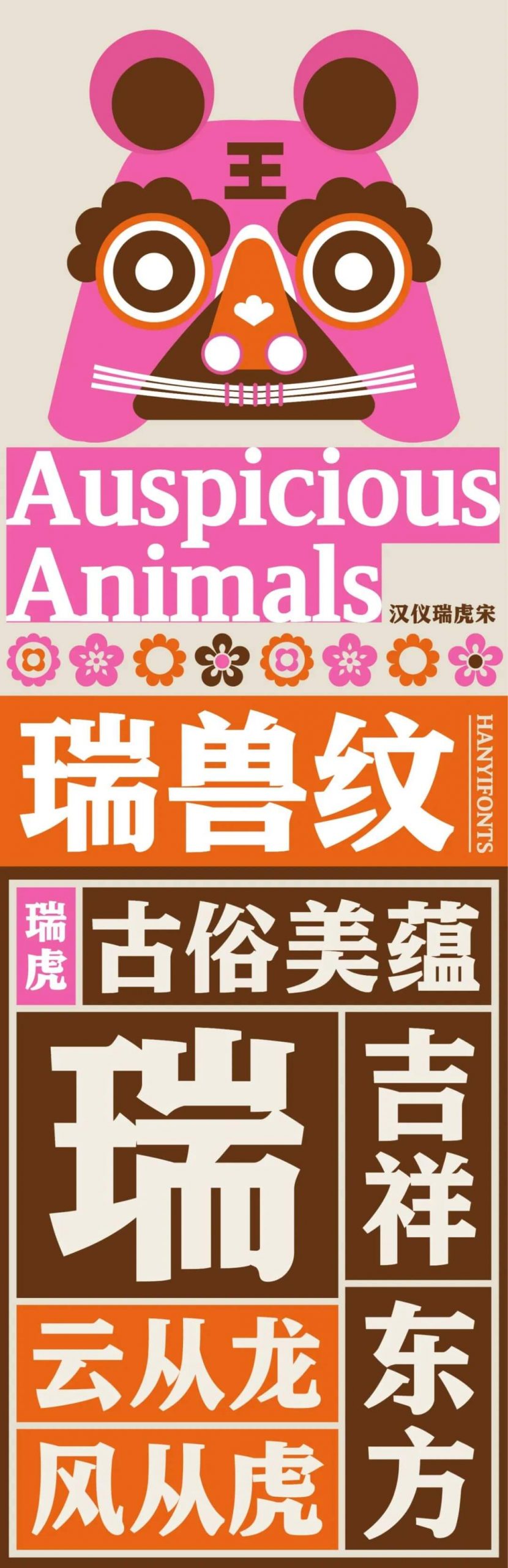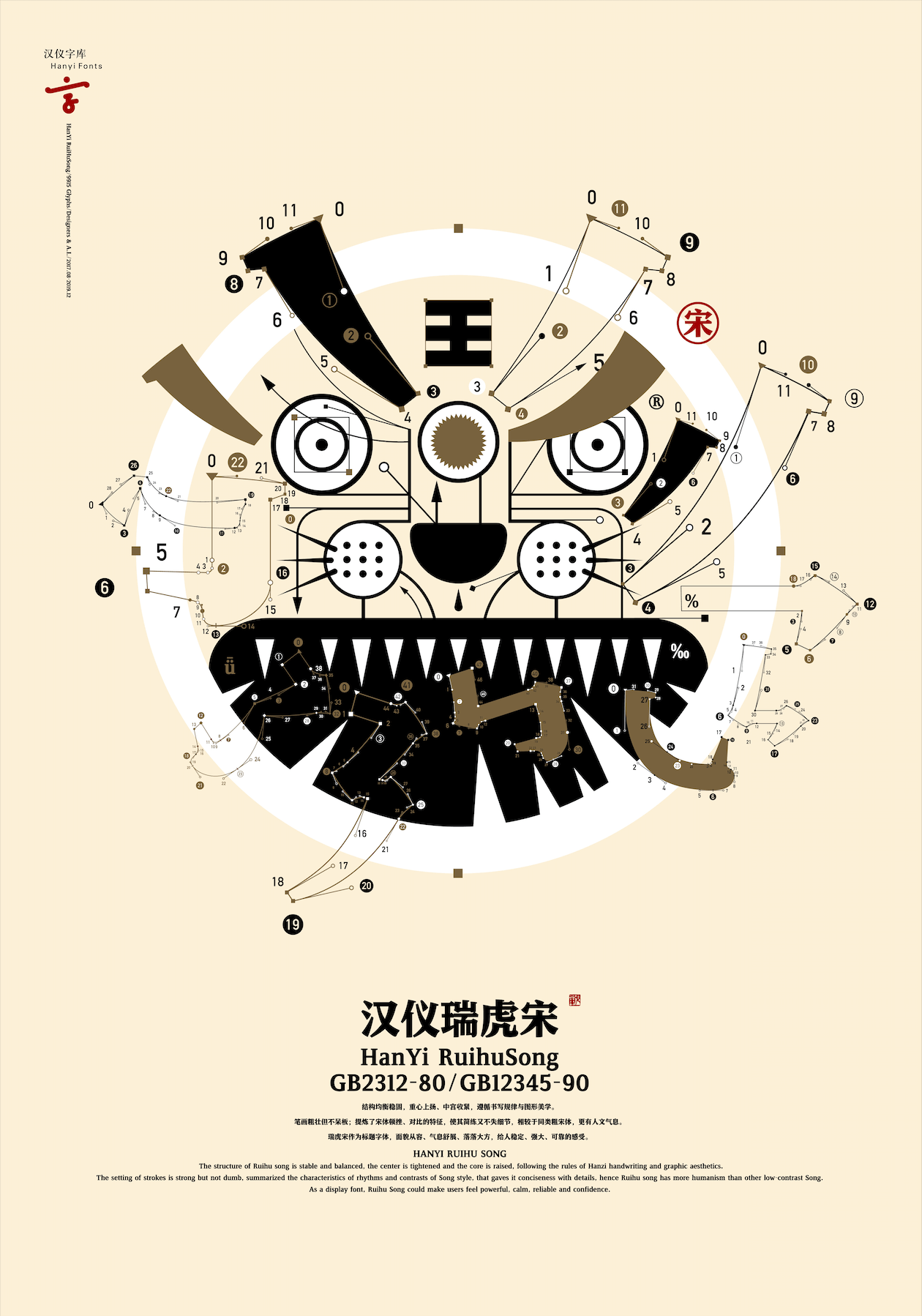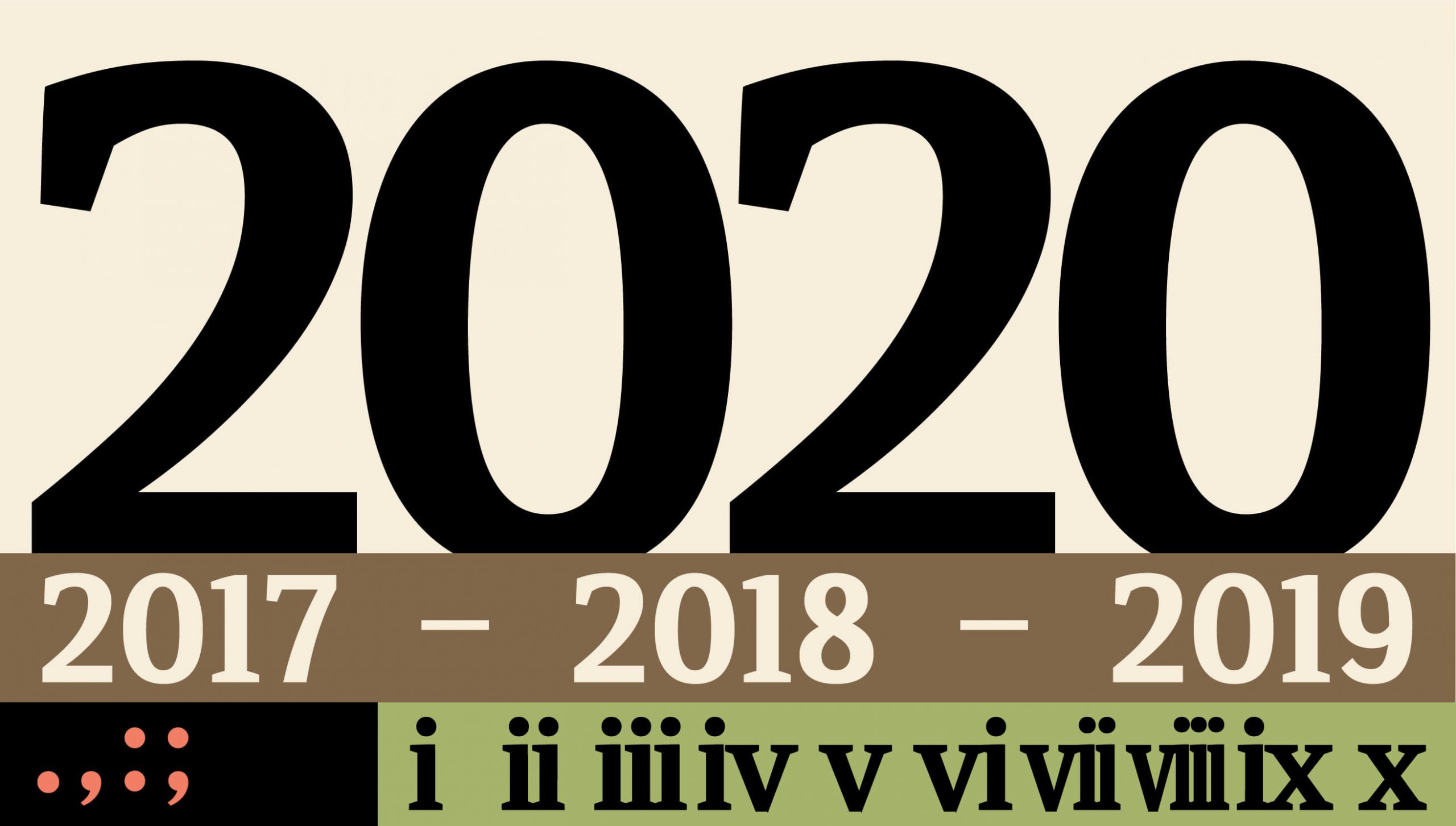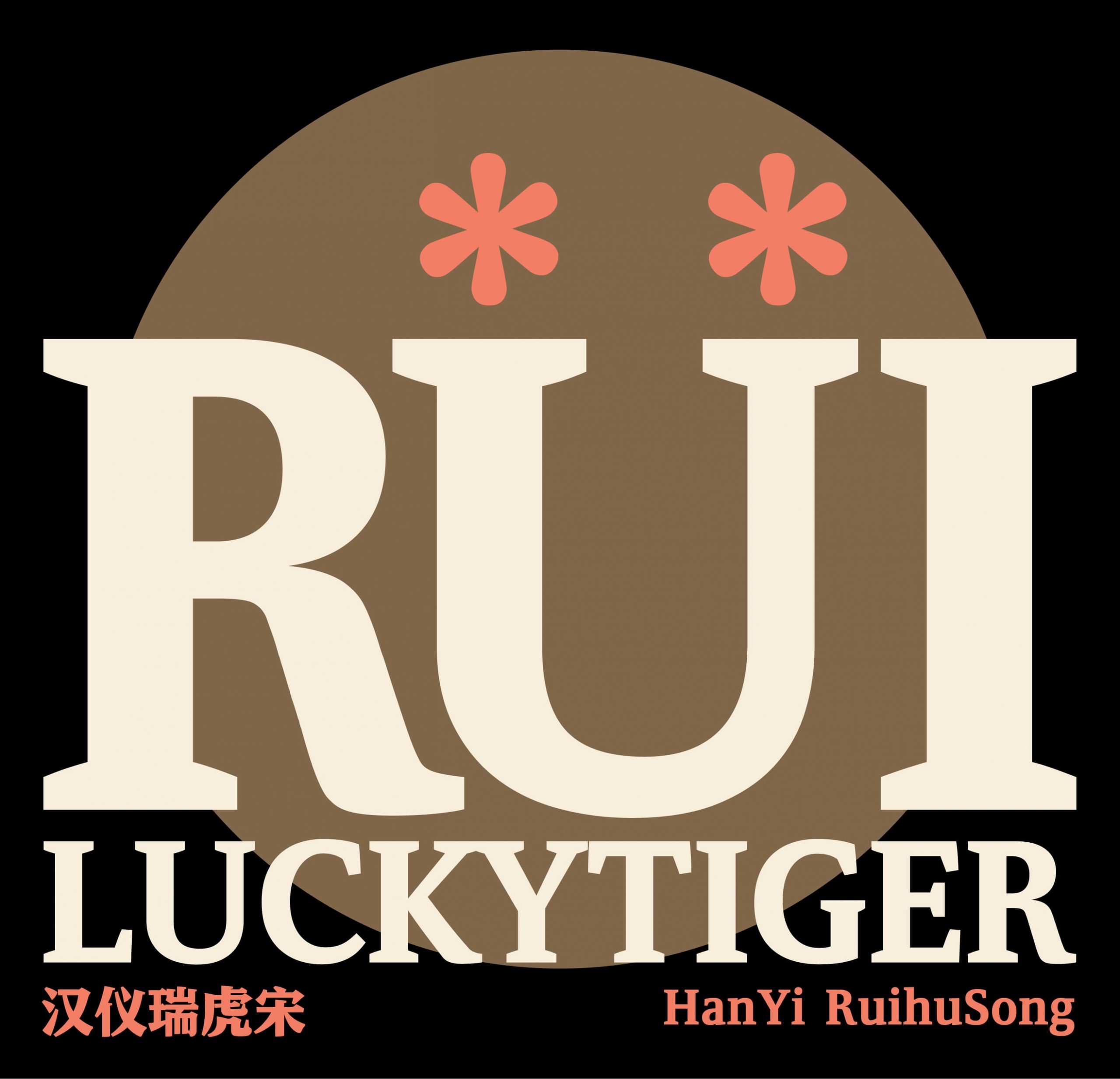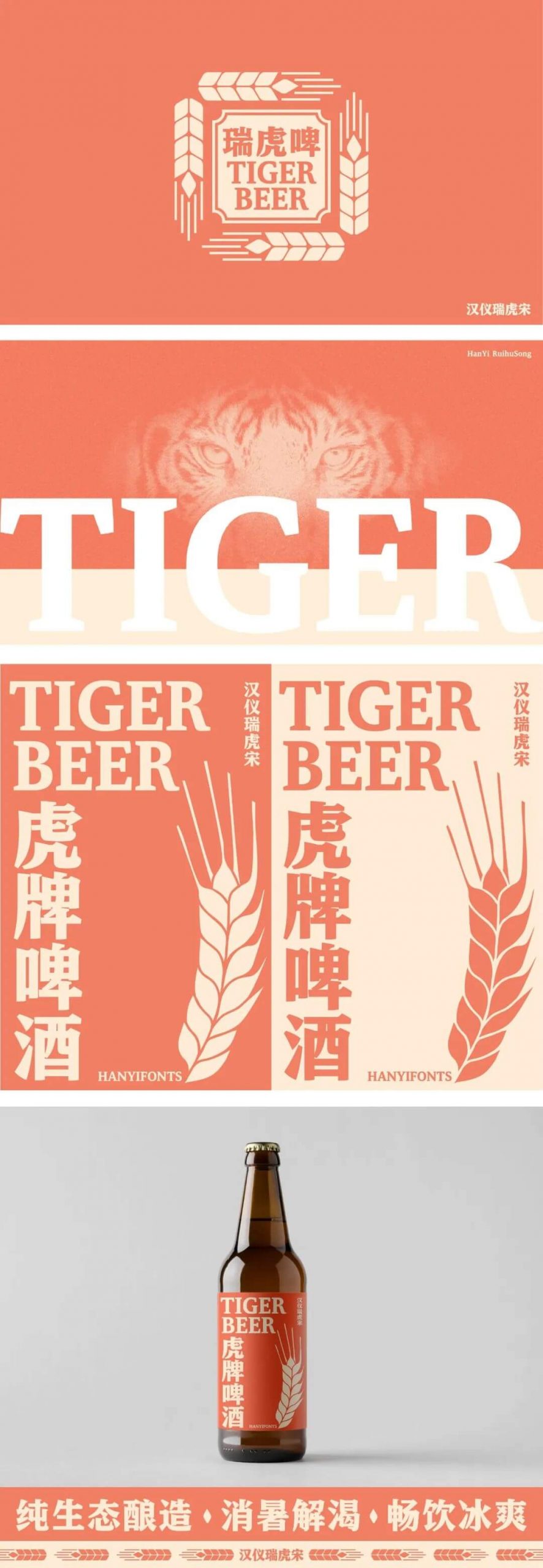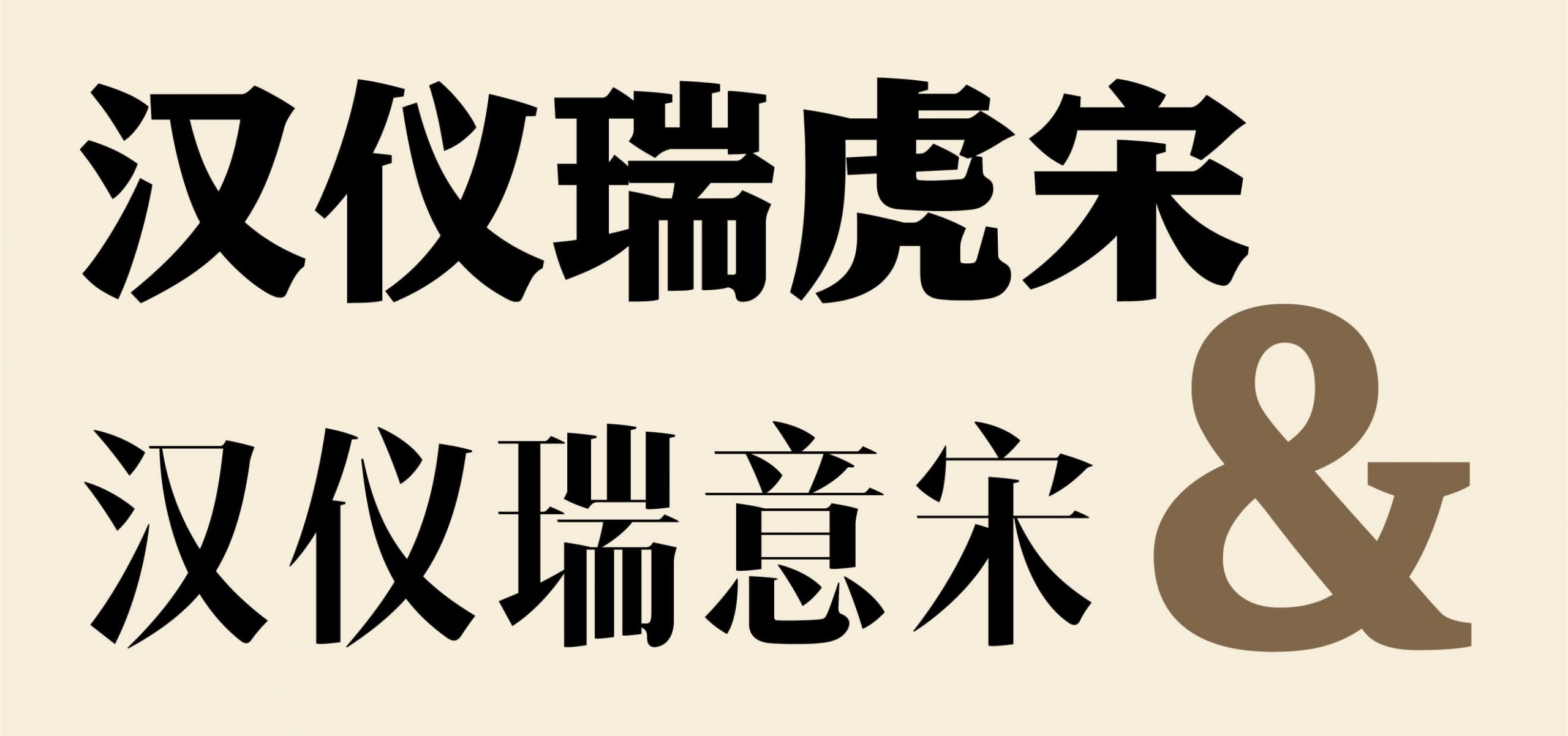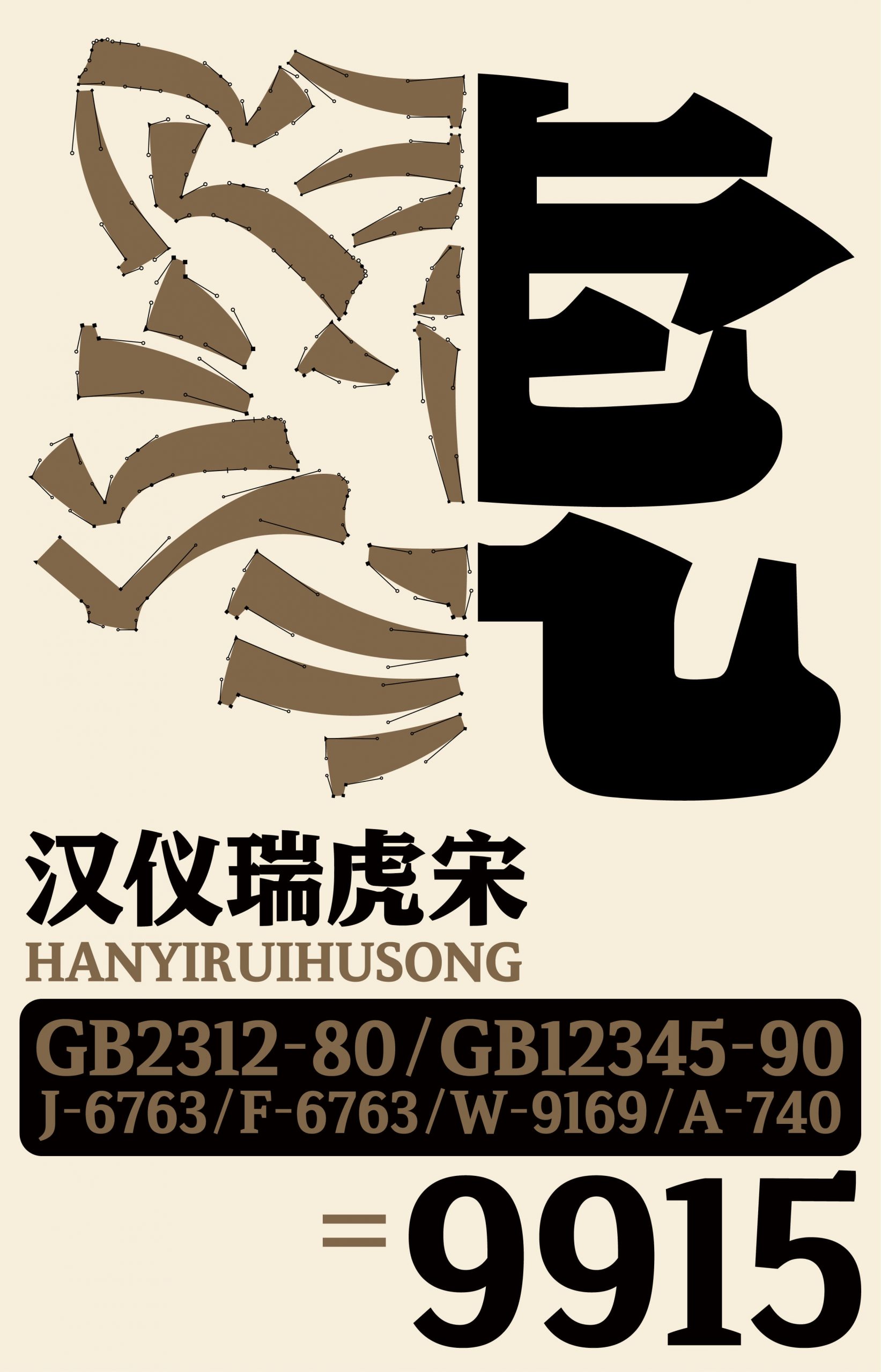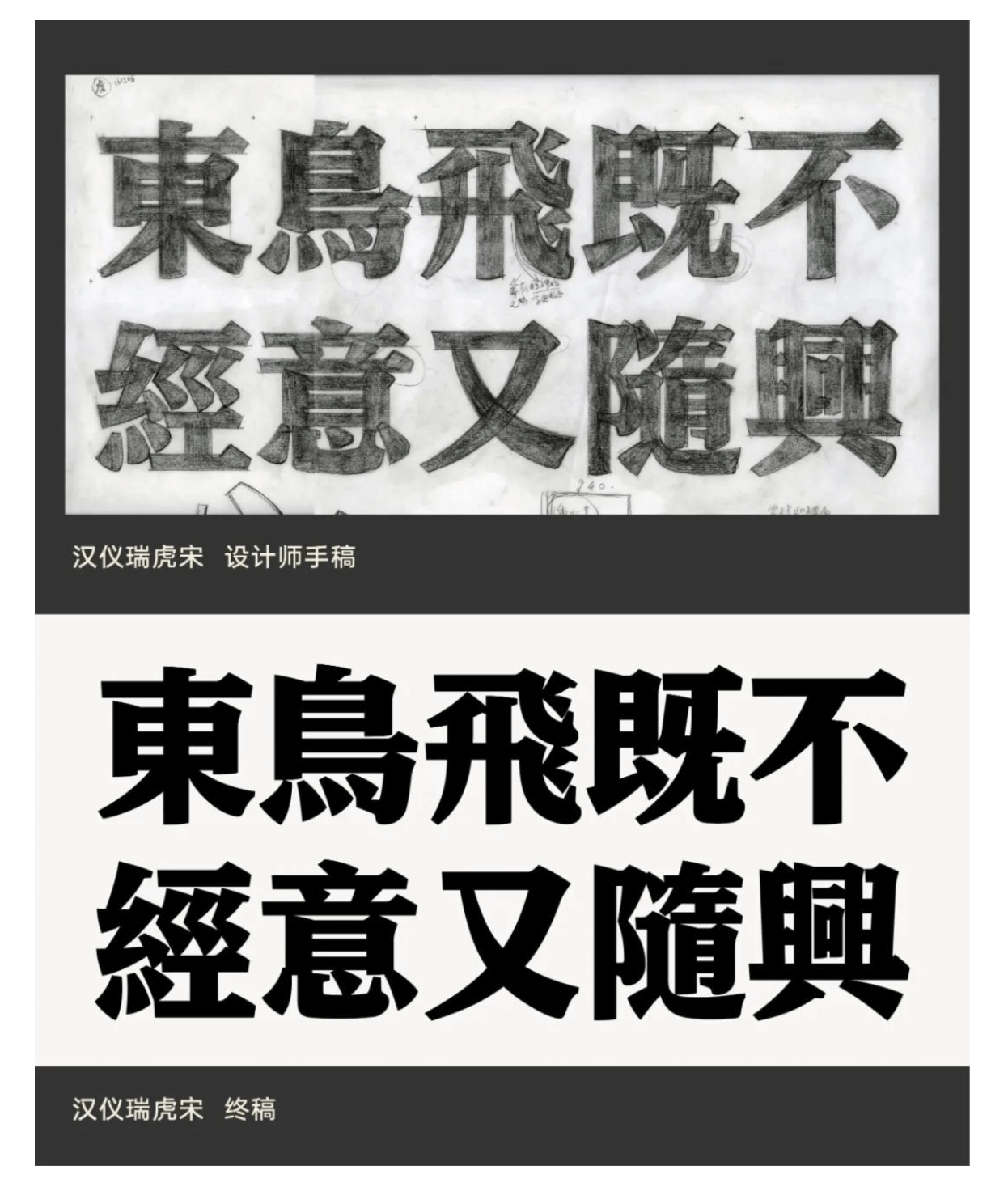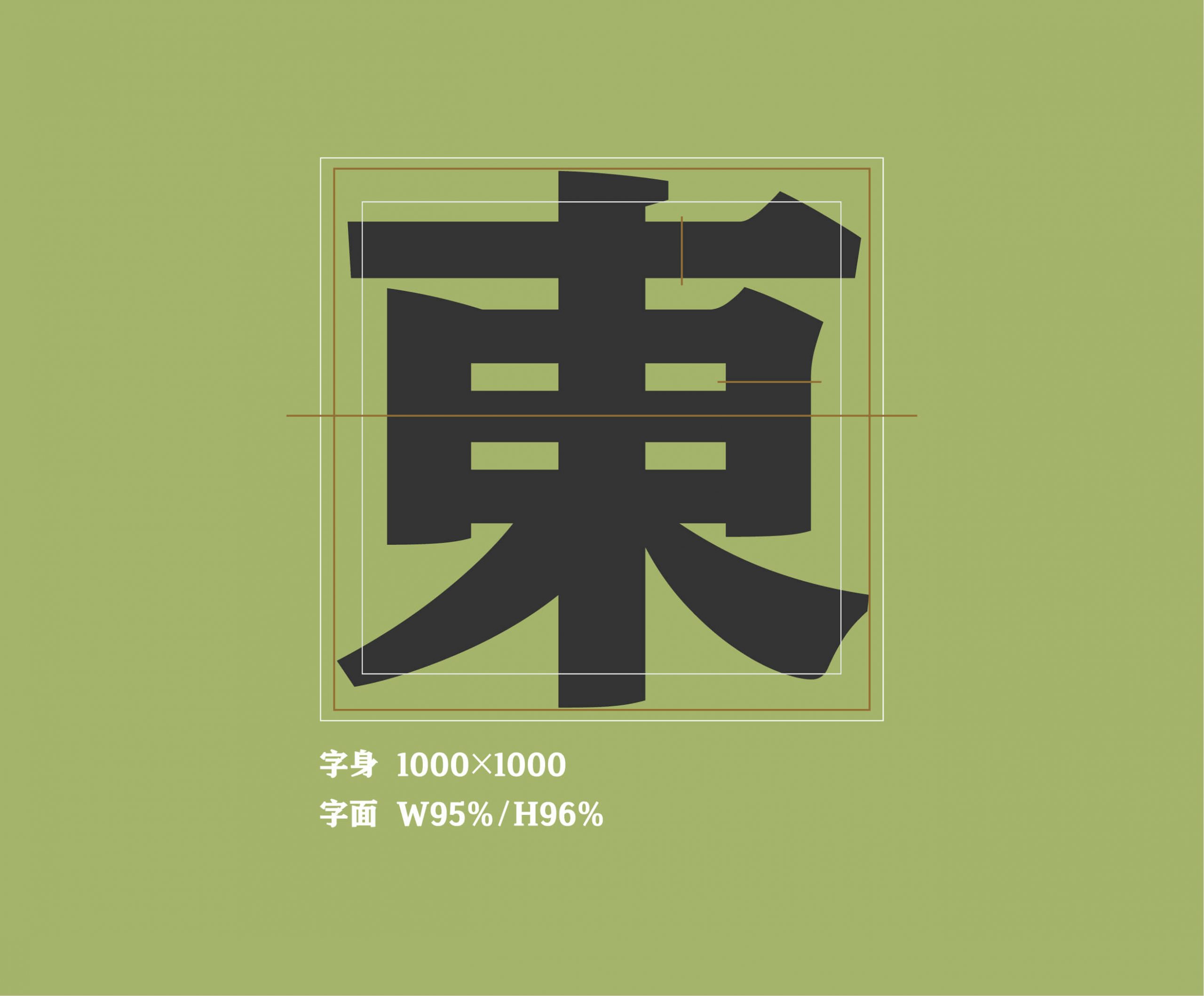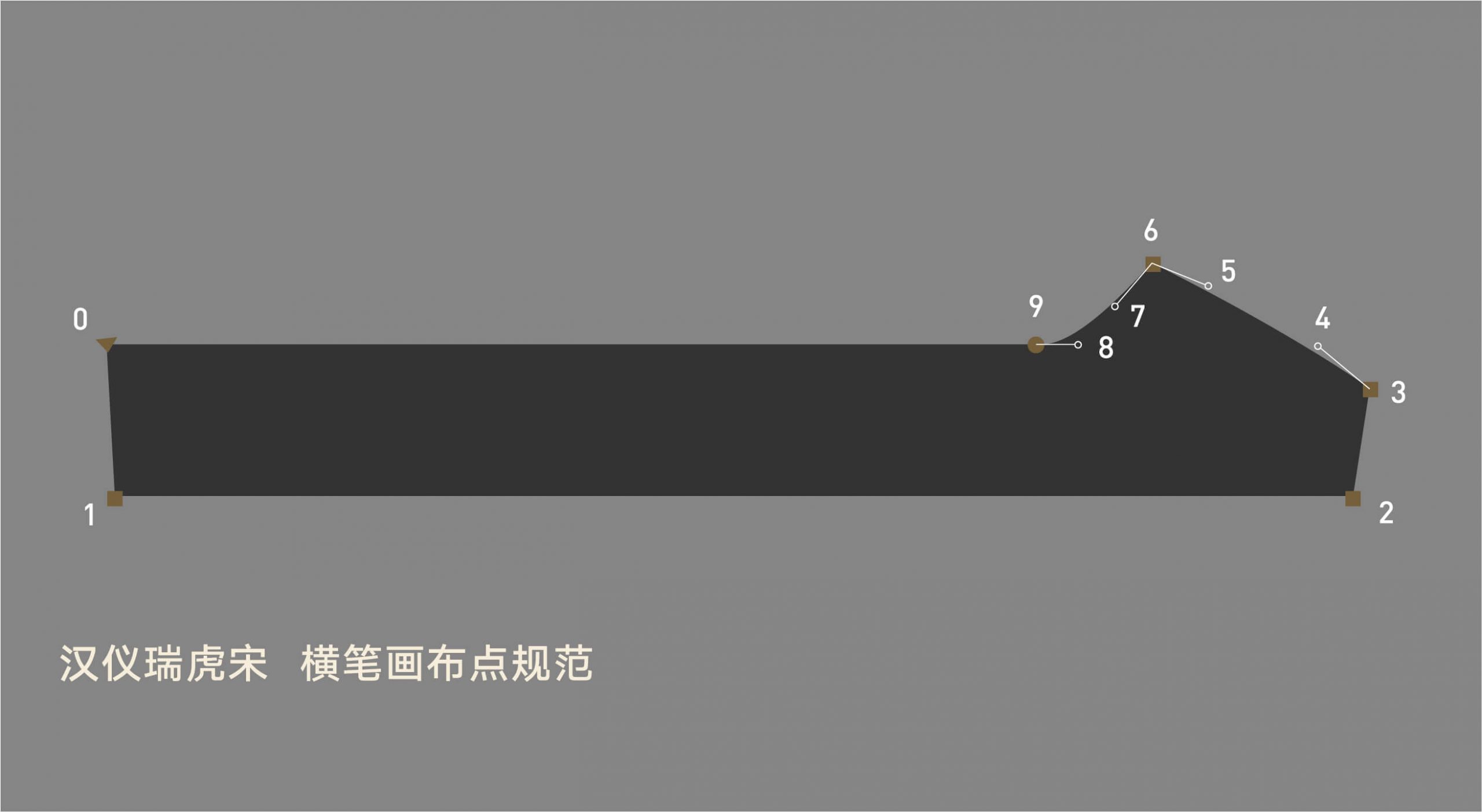
汉仪瑞虎宋体W
设计师战国栋
汉仪瑞虎宋 | 字行虎步
汉仪瑞虎宋是汉仪字库签约设计师战国栋继“汉仪瑞意宋”之后主创的第二套字库,同样是宋体字,但不同于汉仪瑞意宋高挑、时尚的气质,汉仪瑞虎宋则展现出一种厚重、强大的气势,就像是字体名字“虎”一样,有着虎步龙行的态势。
汉仪瑞虎宋自2017年立项以来,设计团队经历了两年多的打磨,共创作了9915个字符,涵盖中文简繁、网络常用字、拉丁字符及日文假名等。
汉仪瑞虎宋 | 整体特点
这款字体凝练了宋体字的特质,融入了设计师独特的设计概念,呈现出一种厚实稳重、气息舒展,又颇具人文气质的面貌,是一款设计精细,适用性非常强的宋体标题字。
汉仪瑞虎宋 | 字形结构
汉仪瑞虎宋作为一款宋体标题字,结构清晰易读,有着非常强的识别性。从整体结构来看,这款字体均衡稳固,重心偏高,中宫内敛。给人稳定、可靠的感觉。
汉仪瑞虎宋 | 笔画特征
汉仪瑞虎宋细节考究,每一个笔画的处理都非常精心到位,值得深度推敲。
设计师提炼了宋体字笔画特征的顿挫感,让笔画看起来粗壮但不呆板,简练而不失细节。
汉仪瑞虎宋弱化了宋体字横竖笔画对比的强度,作为标题字使用,从视觉上来看更加稳定有力。笔画的处理方式,使其相对比其他的宋体字来说,也显得更具有人文气息。
汉仪瑞虎宋 | 西文符号
汉仪瑞虎宋的西文及符号部分根据中文字体的特征进行了匹配设计。
西文字体设计同样弱化了笔画间的对比度,增强了力量感。曲线的设计富有弹性,线条虽粗壮但却灵活不死板。
西文部分衬线的设计使字体在排列应用的时候形成了清晰的视线引导,造型简洁,工整易读,同时,较大的字怀设计也让字体看起来更加清晰。
汉仪瑞虎宋 | 应用展示
宋体字基于中国传统文化的积淀有着强烈的文化气息,而这款汉仪瑞虎宋则诞生于现代设计思维及审美意识下,两者的碰撞赋予了这款字体更丰富的表现力。
汉仪瑞虎宋 | 设计团队
主创设计师 战国栋
中文团队
西文团队
AI团队